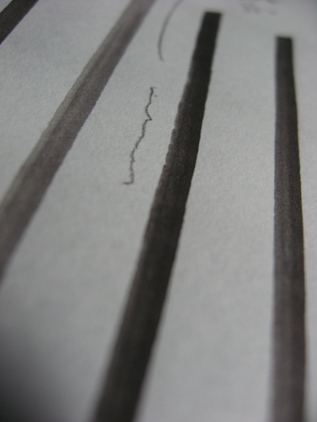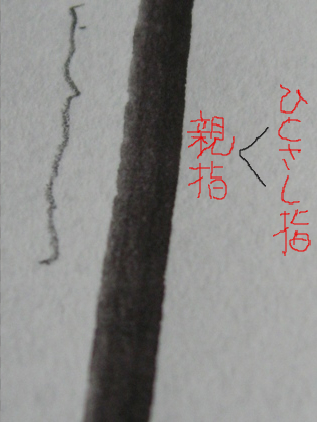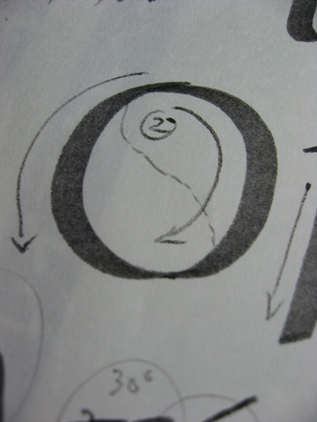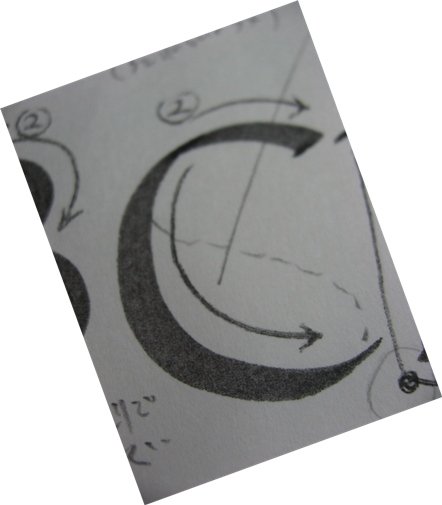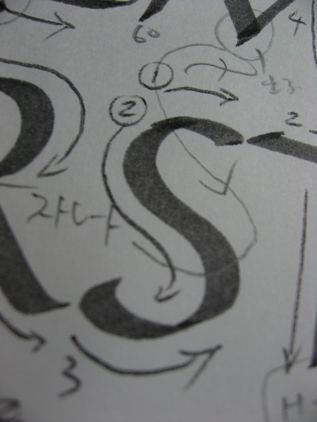
Finding Enjoyment in Writing
mojitor-s¤µ¤ó¤¬¿§¤Ç¥¥ã¥Ï¥¥ã¥Ï&¥¦¥ë¥¦¥ë¤·¤Ê¤¬¤é¤â¡¢
ÁÇÀ²¤é¤·¤¤»ØÆ³¤ò¤·¤Æ¤¤¤ë¤ªÎÙ¡Ä¡£
mojitor-h¤Ï¡¢½ñ¤¤¤Æ¤Þ¤·¤¿¡Ä¡£¡¦¡¦¡¦¤«¡¦¤¡¦¤¿¡¦¤¤¡¦¡ª
º£²óKLAS¤ÎWS ¤Ç¤Ï¡¢Á°È¾¡¢¸åȾ¤È¤âEwan¤Î¥¯¥é¥¹¤ò¼õ¹Ö¡£
ºÇ¶á¤æ¤Ã¤¯¤ê¤È½ñ¤¯»þ´Ö¤â̵¤¯¡¢¤³¤ÎÆü¤ò¿´ÂÔ¤Á¤Ë¤·¤Æ¤¤¤¿¤Î¤Ç¤·¤¿¡£
¡ÖFinding Enjoyment in Writing¡×¡¦½ñ¤¯³Ú¤·¤µ¤ò¸«¤¤¤À¤¹¡¦
Ewan¤¬½é¤á¤ÆÍèÆü¤·¤Æ¤«¤é4ÅÙÌܡʤ½¤Î´Ö10ǯ¡Ë¡¢Ëè²óEwan¤¬
¶µ¤¨¤¿¤¤º¬¤Ã¤³¤ÏÊѤï¤ê¤Þ¤»¤ó¡£
ʸ»ú¤ò½ñ¤¯¤È¤¤Ï¡¢Á´¤Æ¤Î¤³¤È¤Ë¼ª¤ò·¹¤±¡¢¸«¤Ä¤á¡Ä´¶¤¸¤ë¤³¤È¡Ä¡£
ºÇ½ª·ë²Ì¤Ç¤Ï¤Ê¤¯¡¢¡Ö½ñ¤¯¡×¤È¤¤¤¦¹Ô°Ù¤½¤Î¤â¤Î¤ò³Ú¤·¤ß¡¢´î¤Ó¤ò
¸«¤Ä¤±¤ë¤³¤È¡Ä¡£¥í¡¼¥Þ¥ó¥¥ã¥Ô¥¿¥ë¤ò½ñ¤¤Þ¤¹¤¬¡¢´ö²¿³Ø¤Ç½ñ¤¤¤Á¤ã¤¢¤¤¤±¤Þ¤»¤ó¤¾¡Ä¡£¥¤¥ó¥Ê¡¼¥¹¥Ú¡¼¥¹¤Ï¤¿¤À¤Î¶õÇò¤¸¤ã¤Ê¤¤¤ó¤Ç¤¹¤è¡ª¤½¤ÎÃæ¤Ï¤É¤Ã¤·¤ê¤·¤Æ
¥¨¥Í¥ë¥®¡¼¤¬Ëþ¤¿¤µ¤ì¤Æ¤ë¤ó¤Ç¤¹¤è¡ª
»ä¤¿¤Á¤¬½ñ¤¤¤Æ¤¤¤ëÀþ¤Ïư¤¤¤Æ¤¤¤Þ¤¹¤Í¡Ä¡£Á´¤Æ¤Îư¤¤Ë¤Ï´¶¾ð¤¬¹þ¤á¤é¤ì¤Æ¤¤¤Þ¤¹¡£
¤½¤Îư¤¤«¤é¥¯¥ê¥¨¥¤¥È¤µ¤ì¤¿¤â¤Î¤¬Calligraphy¤Ê¤ó¤Ç¤¹¤è¡£¤½¤ì¤Ï¿¹ÍåËü¾Ý¤ÎÀ¤³¦¤«¤é³Ø¤Ö
¤â¤Î¤Ê¤ó¤Ç¤¹¤è¡Ä¡£
¤½¤Îư¤¤ò¥Þ¥¹¥¿¡¼¤¹¤ë¤Î¤Ë¤Ï¡©
ư¤¤ò¼ÙË⤹¤ë¤â¤Î¤¬¤¤¤í¤¤¤í¤¢¤ê¤Þ¤¹¡£
¡Ö¥¥ã¡¼¡×¤ª¾î¤µ¤ó¡ª¼«Ê¬¤Î½ñ¤¤¤¿Àþ¤ò¤³¤ó¤Ê¤ËÀܼ̤·¤¿¤³¤È¤¬
¤¢¤ê¤Þ¤¹¤«¡©ÌÓ·ê¤âÉݤ¤¤¬¤³¤ì¤âÉݤ¤¡Ä¡£
°ì¿Í¡¢°ì¿Í¡¢»Ø¤ÎŤµ¤â°ã¤¦¤·¡¢Êʤ⤢¤ë¡Ä¡£
¤â¤·¡¢¤¢¤Ê¤¿¤¬¤³¤Î¤è¤¦¤ËÀþ¤Îº¸Â¦¤¬¥®¥¶¥®¥¶¤·¤Æ¤¤¤¿¤é¡¢
»Ø¤ÎÎϤΥХé¥ó¥¹¤¬Êø¤ì¤Æ¤¤¤ë¾Úµò¤Ç¤¹¡£
¿Æ»Ø¤è¤ê¤Ò¤È¤µ¤·»Ø¤ÎÎϤÎÊý¤¬¶¯¤¤¤Î¤Ç¤¹¡£¤³¤ì¤Ëµ¤¤Å¤¤¤¿¤é
ξ»Ø¤ÎÎϤò¶ÑÅù¤Ë¤Ê¤ë¤è¤¦¤Ë¿´¤¬¤±¤Þ¤·¤ç¤¦¡ª
¤â¤·¤«¤·¤¿¤é»ÑÀª¤¬°¤¤¤Î¤«¤â¤·¤ì¤Þ¤»¤ó¡Ä¡£´ù¤Î¹â¤µ
¹ç¤Ã¤Æ¤Þ¤¹¤«¡©Î¾Â¤Ï¤Á¤ã¤ó¤È¾²¤Ë¤Ä¤¤¤Æ¤Þ¤¹¤«¡©
°Ø»Ò¤Ë¤Ï¤Á¤ã¤ó¤È¿¼¤¯ºÂ¤Ã¤Æ¤Þ¤¹¤«¡©
Ewan¤Ï°ì¿Í¤º¤Ä½ñ¤¤¤Æ¤ë»Ñ¤ò¼Ì¿¿¤Ë»£¤ê¡¢¤É¤³¤Ëµ¤¤ò¤Ä¤±¤ë¤«¥¢¥É¥Ð¥¤¥¹¤·¤Æ¤¯¤ì¤Þ¤·¤¿¡£
´ù¤¬¾¯¤·¹â¤¤¤Î¤Ç°Ø»Ò¤ò¤â¤¦°ì¤Ä
½Å¤Í¤ÆÄ´À°¤·¤Þ¤¹¡£¤½¤¦¤¹¤ë¤È¤¬
É⤯¤Î¤Ç¡¢¿·Ê¹»æ¤òÉߤ¤¤ÆÂ¾ì¸Ç¤á¡ª°Ø»Ò¤â¿¼¤á¤ËºÂ¤Ã¤Æ°ÂÄꤷ¤Æ¤¤¤Þ¤¹¤Í¡£
¤½¤¦¤¹¤ë¤È¡¢¤É¤¦¤Ç¤·¤ç¤¦¡Á¡£±¦ÏӤμê¼ó¤«¤éɪ¤Þ¤ÇÃúÅÙÎɤ¤Ä¹¤µ¤Ë¤Ê¤ê¤Þ¤·¤¿¡£Ã»¤¹¤®¤ë¤È¡¢
¼ê¤ÎưºîÈϰϤ¬¶¹¤Þ¤ê¤Þ¤¹¡£Ä¹¤¹¤®¤ë¤È¼ê¤ËÎϤ¬¤¦¤Þ¤¯ÅÁ¤ï¤ê¤Þ¤»¤ó¡£»æ¤Î¾å¦¤Ë¤Ï²¿¤«Êª¤ò
ÃÖ¤¤¤Æ¤Ï¤¤¤±¤Þ¤»¤ó¤è¡ª¾ï¤Ë¼«Ê¬¤¬½ñ¤¯¤â¤Î¤ÎÃæ¿´¤Ë¤¤¤ë¤³¤È¤Ç¤¹¡ª
¤è¤¯°Ø»Ò¤ËÀõ¤¯ºÂ¤ë¿Í¤¬¤¤¤Þ¤¹¤¬¡¢¤³¤ì¤Ï´ù¤¬¹â¤¹¤®¤ë¤«¤é¡¢¼«Ê¬¤¬Á°¤ÎÊý¤Ë¤º¤é¤·¤ÆºÂ¤Ã¤Æ
¤·¤Þ¤¦¤Î¤Ç¤¹¡£¤³¤ì¤Ç¤Ï»ÑÀª¤¬°¤¯¤Ê¤ê¤Þ¤¹¡ª
¤µ¤Æ¡¢Ãæ¤Ë±ß¤ò»ý¤Äʸ»ú¤Ç¤¹¤¬¡¢
²èÁü¤Î¤è¤¦¤Ë¡¢¤Ä¤Ê¤®Ìܤ˹Ԥ¯
ÅÓÃæ¤Ï¡¢¶õÃæ¤ÇÀþ¤¬¤Ä¤Ê¤¬¤Ä¤Æ¤¤¤ë¤«¤ÎÇ¡¤¯Æ°¤¤Þ¤¹¡ª
½ñÆ»¤Î¤è¤¦¤Ç¤¹¤Í¡ª
¤³¤Îư¤¤¬¡¢¤Ä¤Ê¤®Ìܤò
¤¿¤À¡Ö¤Ä¤Ê¤®¤Þ¤·¤¿¡×¤Ç¤Ï¤Ê¤¯¡¢
¤â¤Ã¤È³Î¼Â¤Ë¡Ö¤Ä¤Ê¤¬¤ê¹ç¤¦¡×
À¤³¦¤Ø¤È¿Ê¤ó¤Ç¤¤¤¯¤Î¤Ç¤¹¡£
ĴϤÎÀ¤³¦¤Ç¤¹¡£
S¤âº£²ó¤Ï´·¤ì¤¿½ñ¤½ç¤Ç¤Ï¤Ê¤¯¡¢Æ¬¤«¤éÀè¤Ë
½ñ¤¤Þ¤·¤¿¡£ÉáÄ̤ϡ¢¢¤«¤é½ñ¤¤Þ¤¹¤¬¡¢¤³¤ì¤À¤È¡¢
Æâ¦¤Î±ß¤Î´Ý¤ß¤ÎÌܰ¤¬¤Ä¤¤Ë¤¯¤¤¤È¤«¡¦¡¦¡¦¡£
³Î¤«¤Ë¡¤ò½ñ¤¤¤Æ¤½¤Î¤Þ¤Þ¥Ú¥ó¤òÎ¥¤µ¤º¡¢Ìᤷ¤Æ
¤½¤Î¤Þ¤Þ¢¤ËÆþ¤ë¤È¤È¤Æ¤â½ñ¤¤ä¤¹¤«¤Ã¤¿¤Ç¤¹¡£
¤è¤¯¡¢Æ¬¥Ç¥Ã¥«¥Á¤Ë¤Ê¤ê¤ä¤¹¤¤S¤Ç¤¹¤¬¡¢¤³¤Î½ç¤Ç
½ñ¤¯¤È¡¢¥Ð¥é¥ó¥¹¤¬¼è¤ê¤ä¤¹¤¤¤Ç¤¹¡ª
»ä¤Ï¡¢¥Ü¥ä¥Ü¥ä¤·¤Æ¤¤¤Æ¡¢¤Û¤È¤ó¤É²èÁü¤¬
»£¤ì¤Æ¤¤¤Þ¤»¤ó¡Ä¡£¡ÊÎÞ¡Ë
Calligraphy¤Î¥¹¥È¥í¡¼¥¯¤È¤Ï¡¢Vitality affects¡¦À¸Ì¿ÎϤÎɽÌ̲½¤òʸ»ú¤Çɽ¸½¤¹¤ë¡Ä¡£
¤Ê¤ó¤Æ¤¹¤Ð¤é¤·¤¤¡Á¡ª¡ª
¥ì¥Ý¡¼¥È¤È¤Ã¤Æ¤âÉü½¬¤Ë¤Ê¤ê¤Þ¤¹¡Á¡Á¡£Ewan¤Ï¤º¤Ã¤È°ì´Ó¤·¤ÆÆ±¤¸»ö¤òÅÁ¤¨¤è¤¦¤È¤·¤Æ¤¤¤ë¤ó¤Ç¤¹¤Í¡¢»ä¤Ïº£²óÆó²óÌܤǤ·¤¿¤±¤É¡¢¤¤Ã¤È¤Þ¤¿¼õ¤±¤Á¤ã¤¦¤À¤í¤¦¤Ê¡¼
S¤Î½ñ¤Êý¡¢Ê¹¤¤¤Æ¤Ê¤«¤Ã¤¿¤è¤¦¤Ç¡¢¤Õ¤Ä¡¼¤Ë½ñ¤¤¤Æ¤Þ¤·¤¿¡Ê¾Ð¡Ë¤³¤³¤Ë½ñ¤¤¤Æ¤¯¤À¤µ¤Ã¤Æ¤¢¤ê¤¬¤È¤¦¤´¤¶¤¤¤Þ¤¹¡ª¤Þ¤¿½ñ¤¤¤Æ¤ß¤Ê¤¯¤Á¤ã¡£
Ewan¤Ã¤ÆËÜÅö¤Ë¶µ¤¨¤ë¤³¤È¤¬Å·¿¦¤ß¤¿¤¤¤Ê¿Í¤Ç¤¹¤Í¤§¡£
°ìÀ¸¶µ¤¨¤Æ¤¯¤À¤µ¤¤¡ª¤Ã¤Æ´¶¤¸¤Ç¤¹¡Ê¾Ð¡Ë¡£
¤¤¤Ä¤â¿´¤òˤ«¤Ë¤·¤Æ¤¯¤ì¤ë¡¢µ»½ÑŪ¤Ê¤³¤È°Ê¾å¤Ë
¤¿¤¯¤µ¤ó¤Î¤³¤È¤¬³Ø¤Ù¤Þ¤¹¡£
Ewan¤¬Í褿¤é¡¢¤Þ¤¿¤´°ì½ï¤·¤Þ¤·¤ç¤¦¤Í¤§¡£